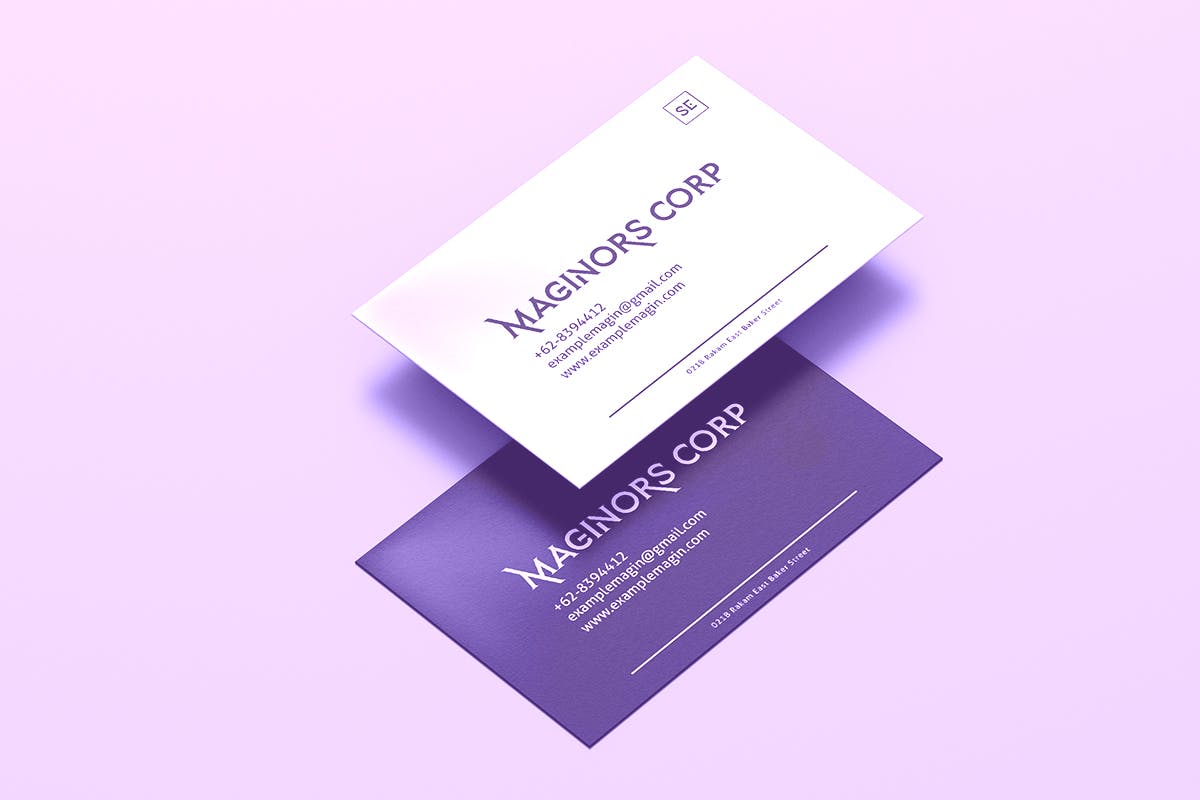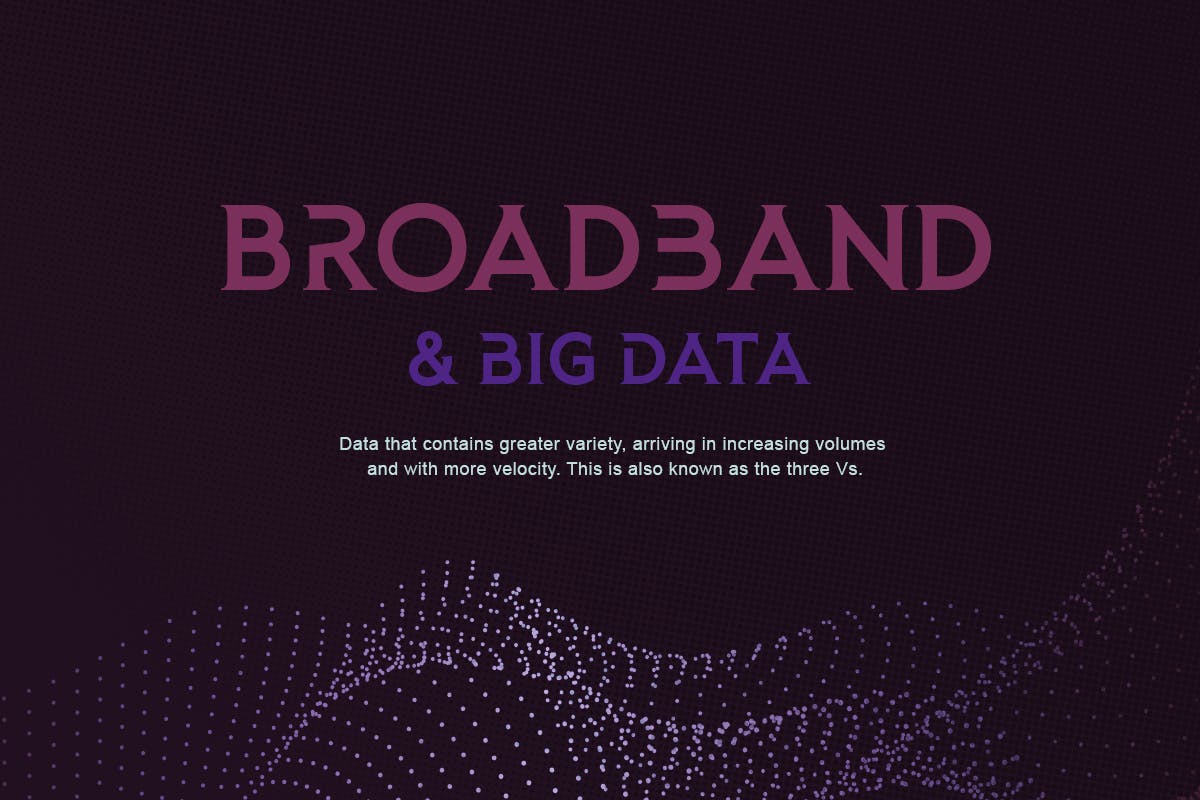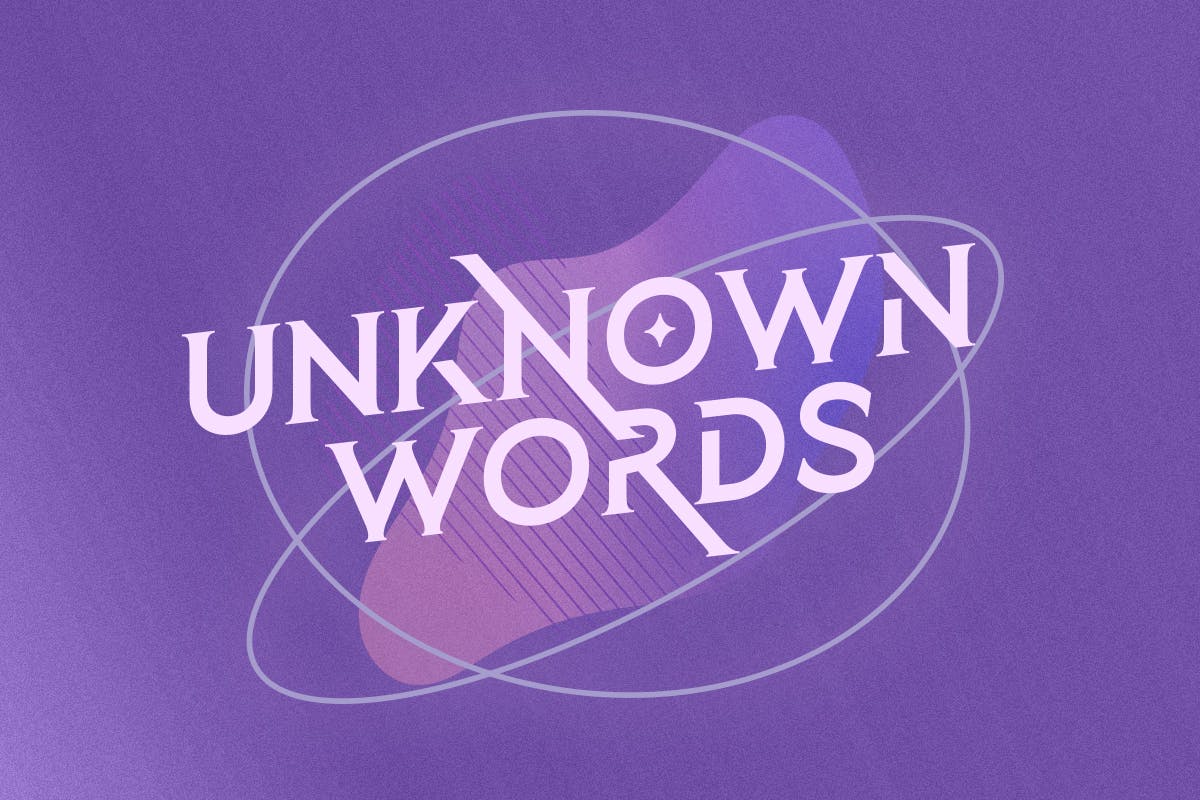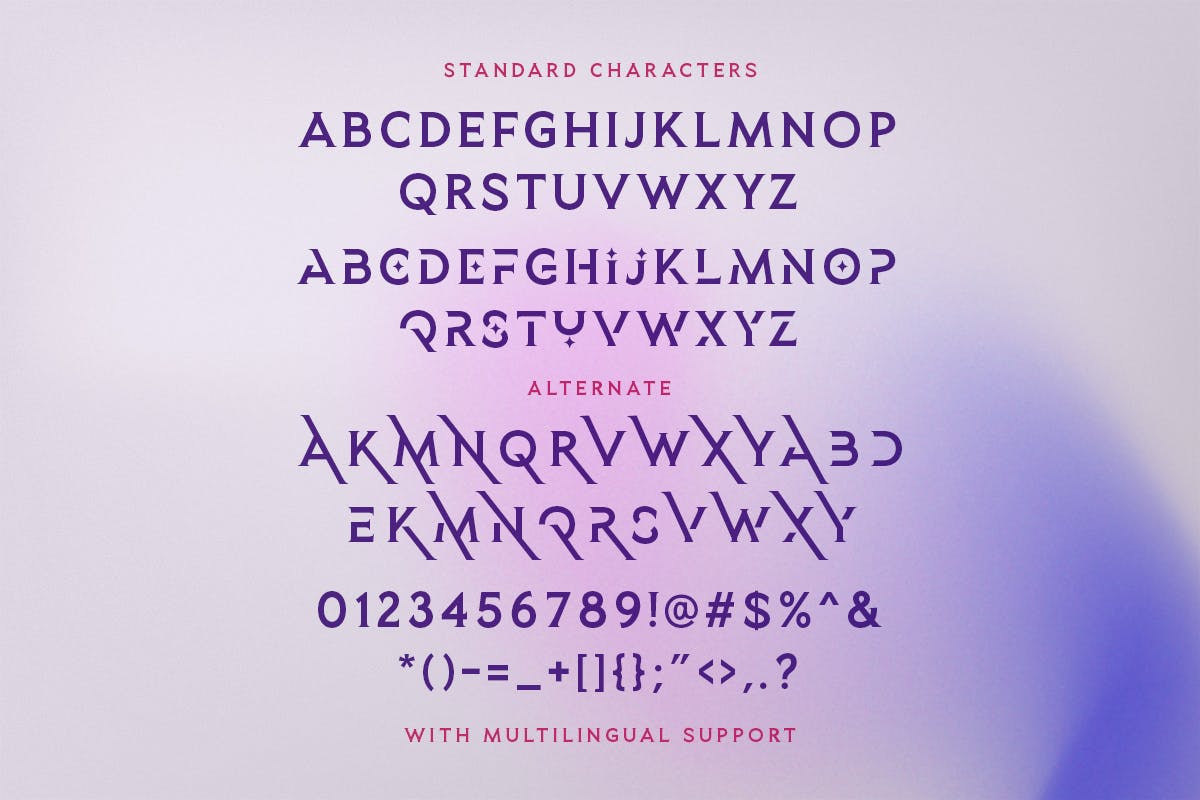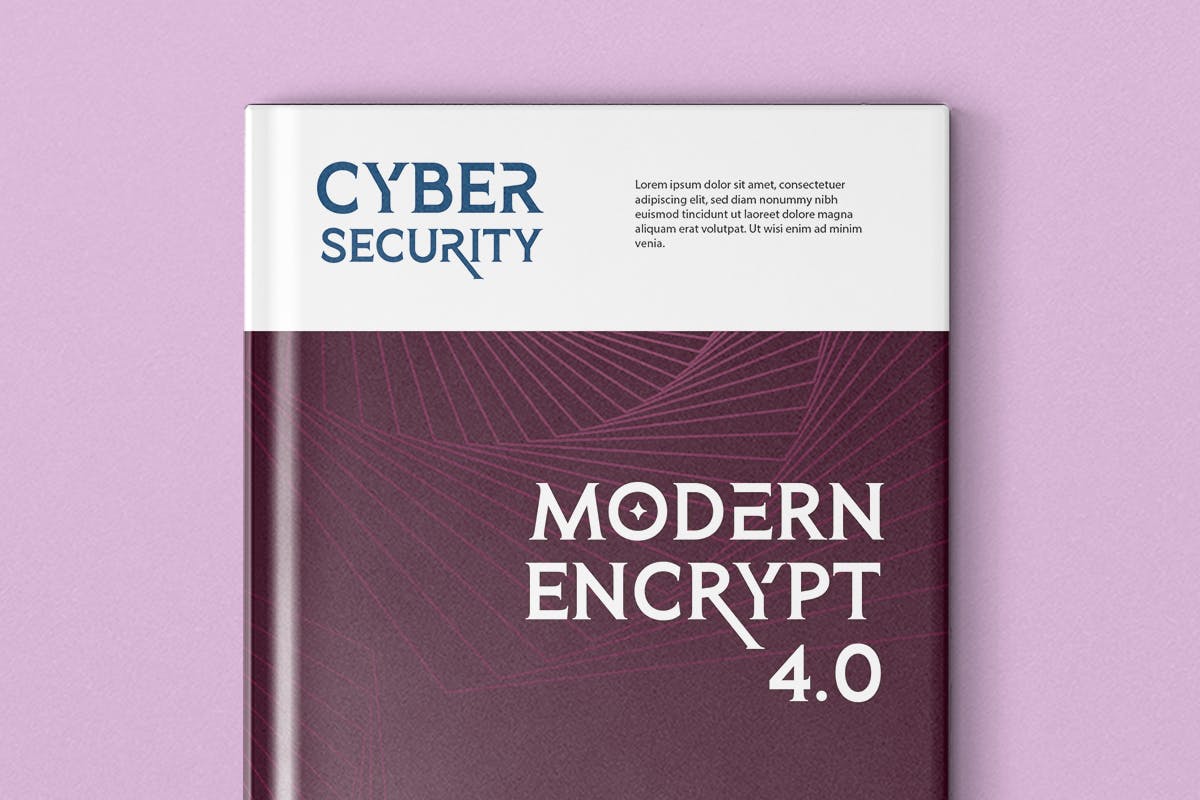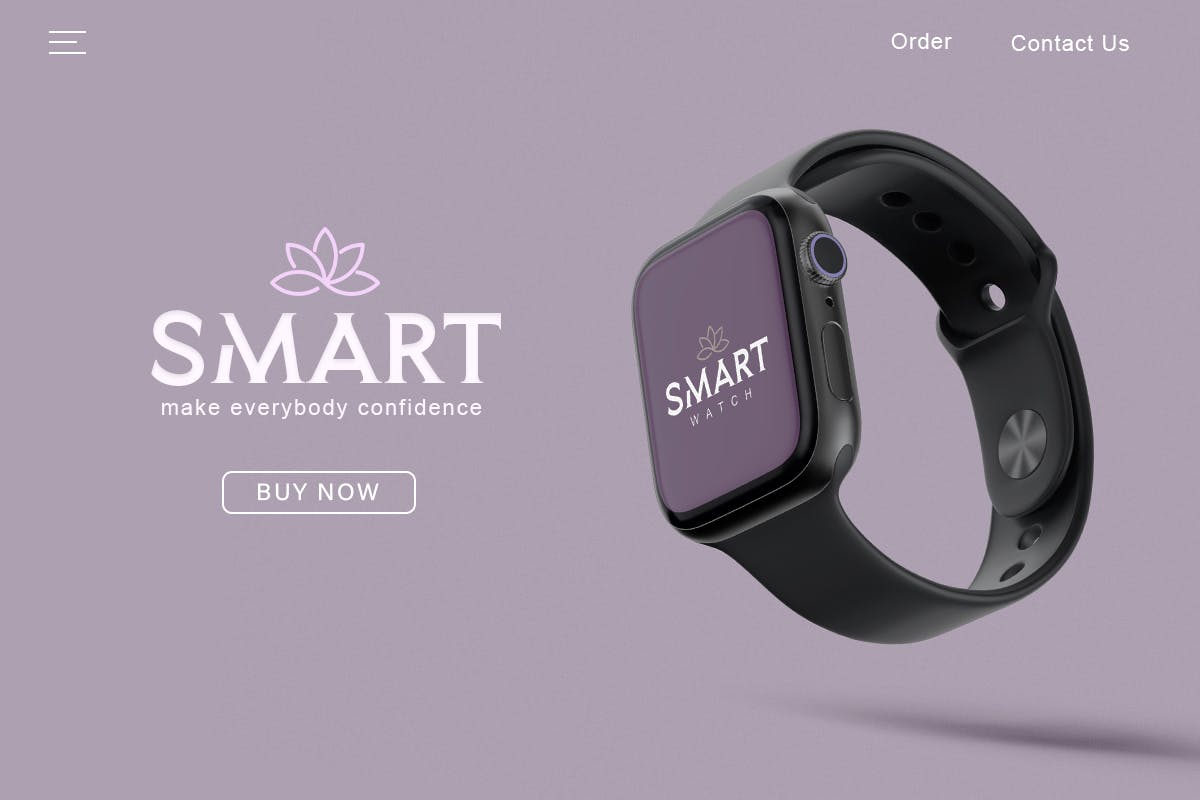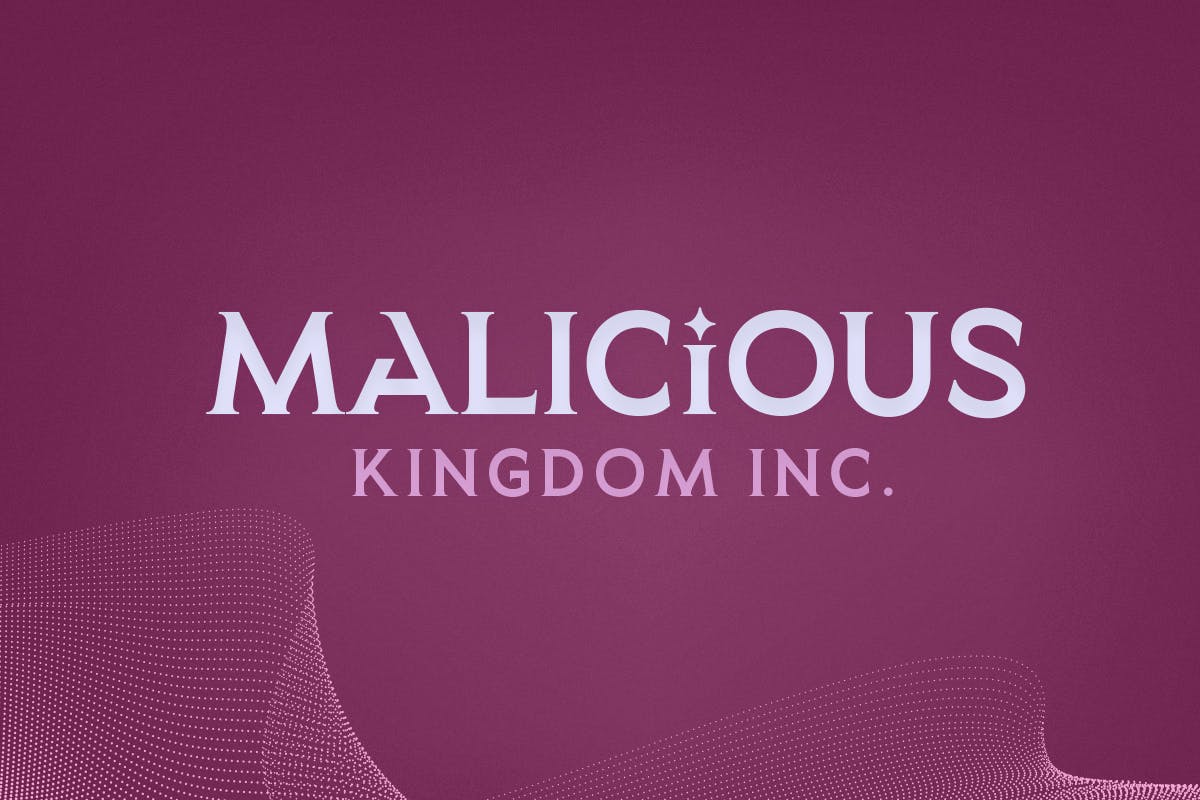
آیا عاشق فونت Blackpast هستید؟ این نسخه serif آن است. معرفی میکنیم، Maginors، یک فونت لوگو مدرن serif با جایگزینهای خاص!
Maginors یک فونت مبتنی بر serif است که با حروف کوچک منحصر به فرد طراحی شده و به طرح شما ظاهری شیک و مدرن میبخشد. با لمس جادوئی این فونت، پروژه شما زیبا و جادویی خواهد شد. میتوانید از این فونت برای هر هدفی استفاده کنید، بهویژه برای طراحی لوگو. میتوانید حروف بزرگ و کوچک را ترکیب کنید تا لوگوی خود را خاصتر کنید. این فونت همچنین دارای جایگزینهای ویژهای است که طراحی شما را بیشتر به چشم میآورد!